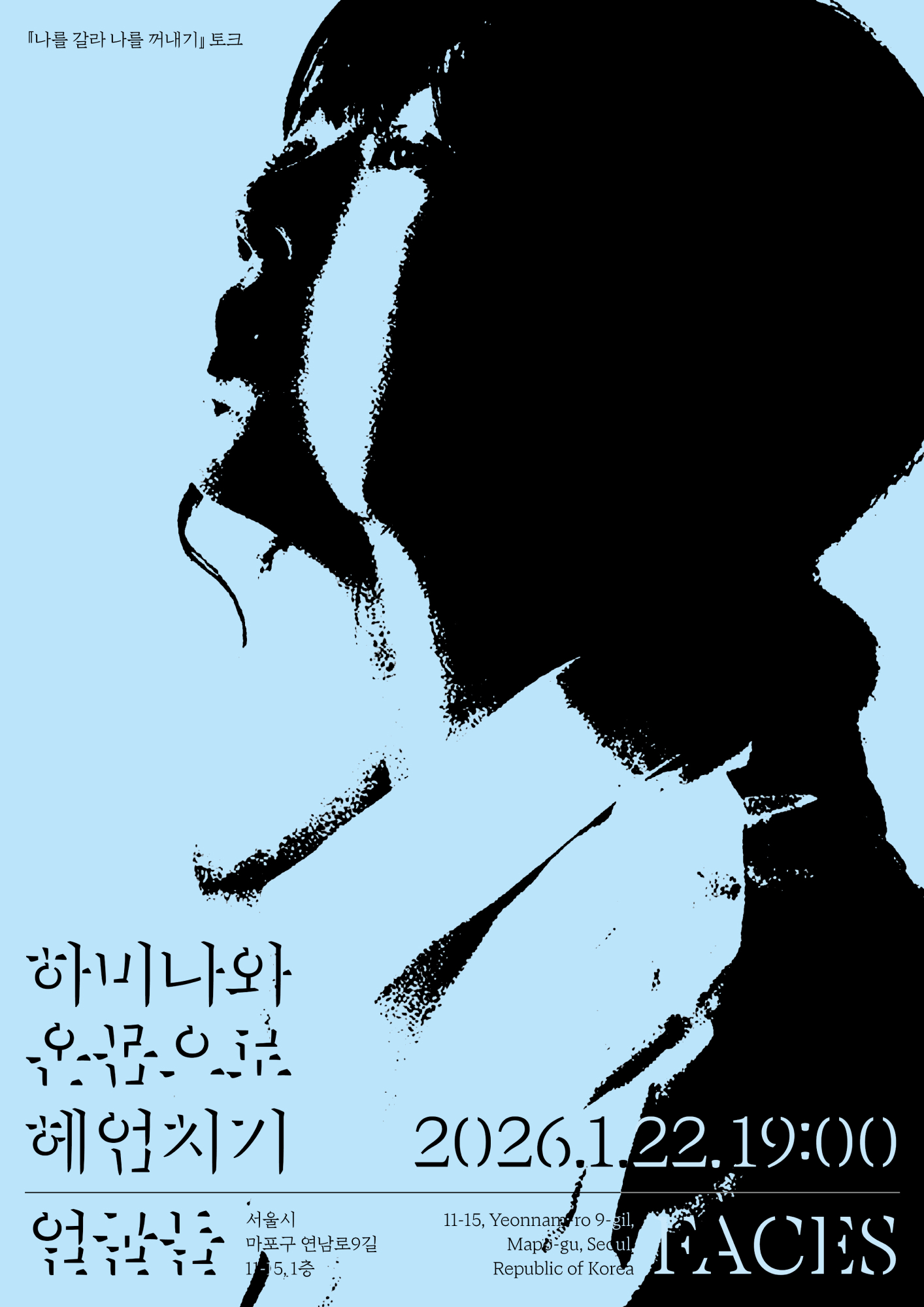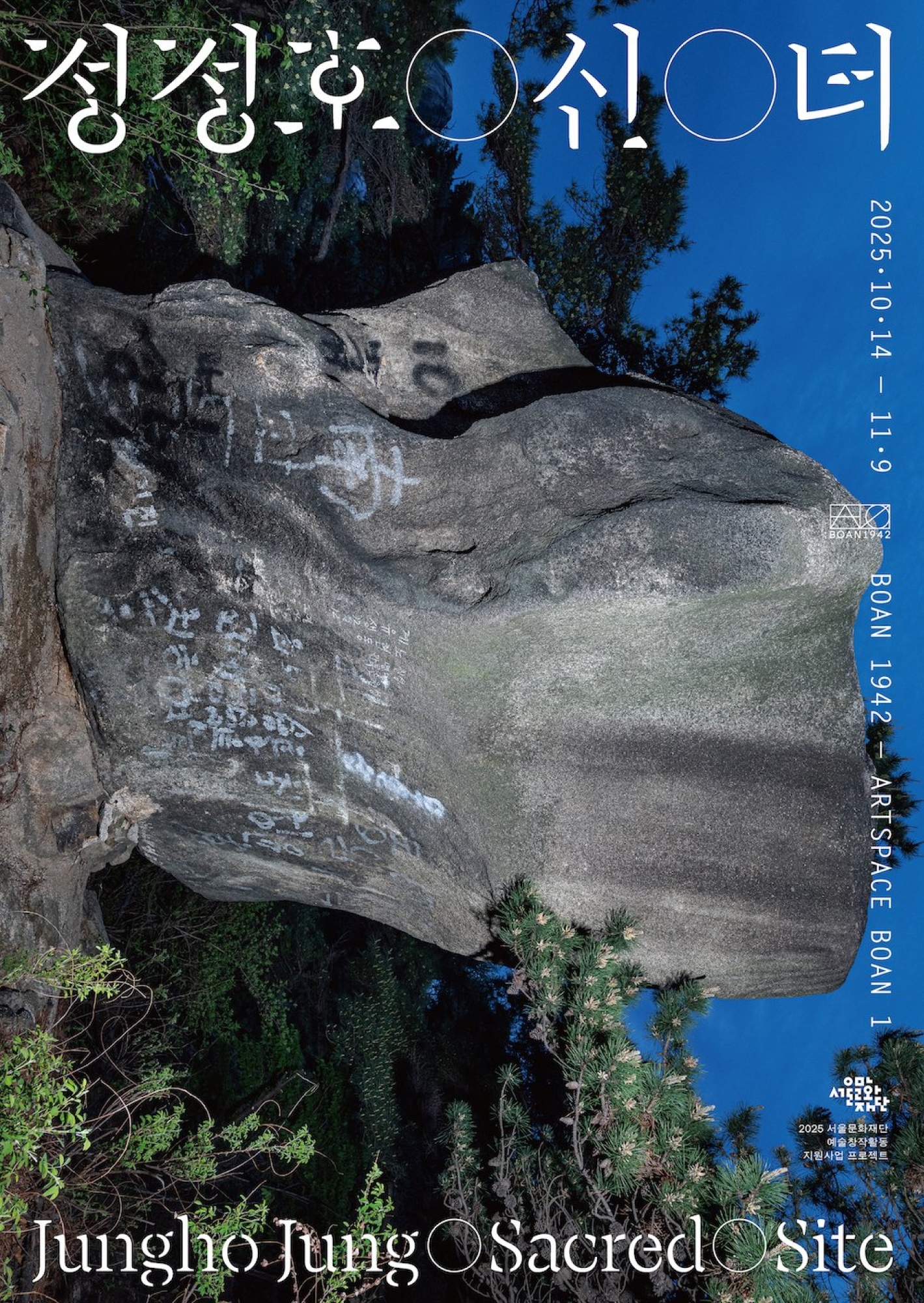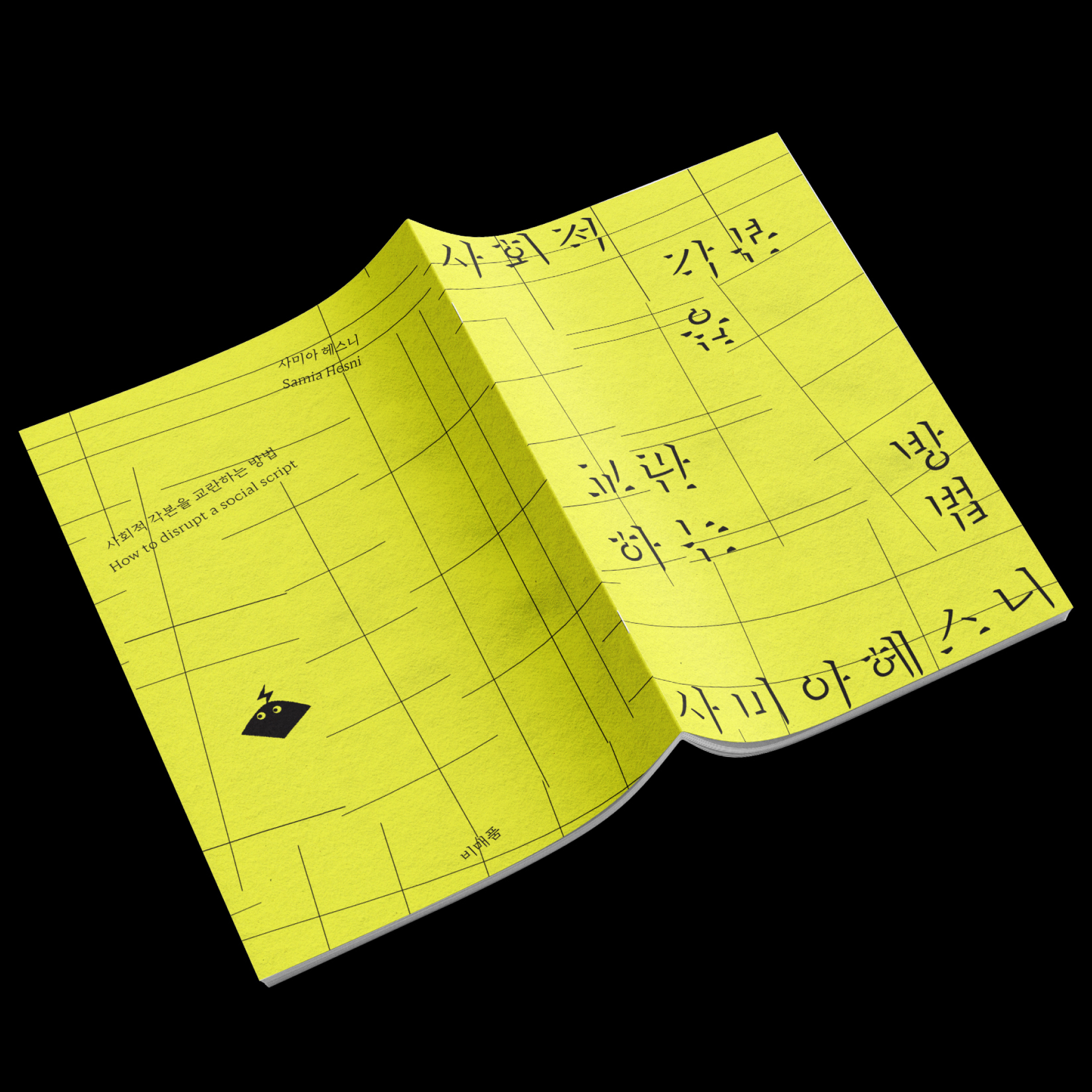
반야 미스트 패밀리
Banya Mist Family
반야 미스트(Banya Mist)는 반야 오리지널이 가진 형태를 유지한채 일부 형태가 사라지는 형상을 띄고 있는 스텐실계열 디스플레이형 글꼴입니다. '반야'가 깨달음의 경지에 이른 초월적 지혜를 뜻하는 거라면, 그 경지의 다다름은 마치 보이지 않는 안개와 같은 느낌이라고 생각했습니다. 반야가 목판본 불경에서 나타난 글자의 형태에서 영감을 받은 것이라면, 반야 미스트는 진리는 안개에 가려져 보이지 않는 듯한 느낌을 글자 형태에 담아보고자 했습니다. 반야와 반야 미스트는 작업에서 서로 쌍으로 사용하면 효과를 더 극대화 할 수 있습니다. 옛 글자의 느낌이 나면서도 또 한편으로는 새로운 인상을 가져오는 서체, 반야 & 반야 미스트(Banya & Banya Mist)를 만나보세요!
반야(Banya)는 전통적인 붓글씨와 목판을 새김을 혼합한 한글 부리계열 글꼴입니다. 이 서체는 20세기 초에 목판본으로 출판된 것으로 추정되는 한 불경에서 영감을 얻어 만들게 된 서체입니다. 전반적으로 나무에 새겨져 샤프하고 단단함 느낌이 듬과 동시에 붓의 쓰임도 같이 느껴져서 섬세하고 독특한 형상을 자아냅니다. 예로들면, 이응의 형태는 마치 붓으로 이어쓴 느낌을 강조한 반면에, 디귿이나 미음에서는 새김의 형태를 도드라지게 하기위해 살짝 스텐실적인 느낌을 가미했습니다. 반야 미스트(Banya Mist)는 반야 오리지널이 가진 형태를 유지한채 일부 형태가 사라지는 형상을 띄고 있는 스텐실계열 디스플레이형 글꼴입니다. ‘반야’가 깨달음의 경지에 이른 초월적 지혜를 뜻하는 거라면, 그 경지의 다다름은 마치 보이지 않는 안개와 같은 느낌이라고 생각했습니다. 반야가 목판본 불경에서 나타난 글자의 형태에서 영감을 받은 것이라면, 반야 미스트는 진리는 안개에 가려져 보이지 않는 듯한 느낌을 글자 형태에 담아보고자 했습니다.